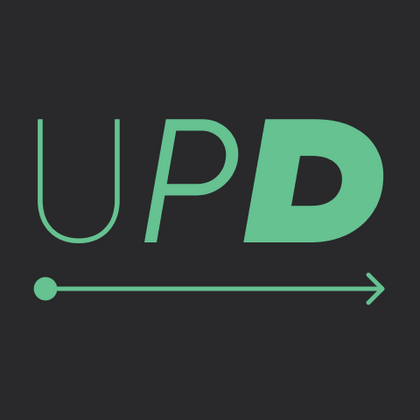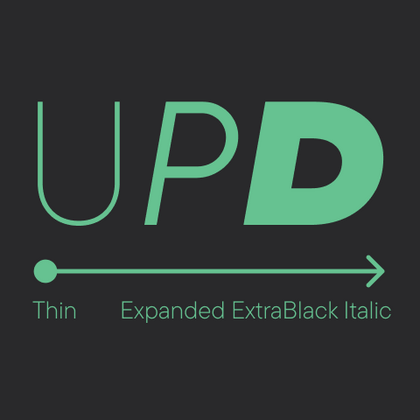
Обновленные шрифты
Коллекция шрифтов TypeType постоянно развивается — мы регулярно улучшаем существующие гарнитуры и расширяем их функциональность. Благодаря этому дизайнеры получают актуальные инструменты с поддержкой современных стандартов типографики.
Среди новинок вы найдете обновленные шрифты с расширенной языковой поддержкой, включая редкие символы и диакритические знаки для разных языков. Каждая такая гарнитура проходит тщательное тестирование, чтобы гарантировать безупречное качество отображения во всех проектах.
TT Norms® Pro — TT Нормс Про
«TT Norms» является зарегистрированным товарным знаком. «Pro» произносится как «про», и является разговорным сокращением слова «профессиональный».
TT Commons™ Pro — TT Коммонс Про
«TT Commons» является зарегистрированным товарным знаком. «Pro» произносится как «про», и является разговорным сокращением слова «профессиональный».
TT Hoves Pro — ТТ Ховс Про
Произносится «ТТ Ховс Про». «Hoves» — производное слово от horizontal (с английского «горизонтальный») и vertical (с английского «вертикальный»). «Pro» произносится как «про», и является разговорным сокращением слова «профессиональный». Буквы «TT» являются аббревиатурой названия компании.
TT Norms® Pro Serif — TT Нормс Про Сериф
«TT Norms» является зарегистрированным товарным знаком. «Pro» произносится как «про», и является разговорным сокращением слова профессиональный. «Serif» произносится как «сериф», в переводе с английского «антиква».
TT Nooks Serif — ТТ Нукс Сериф
Произносится «ТТ Нукс Сериф». «Nooks» — производное слово от nook, в переводе с английского «закоулок». «Serif» произносится как «сериф», в переводе с английского «антиква». Буквы «TT» являются аббревиатурой названия компании.
TT Nooks Serif — акцидентная новостильная антиква с лёгким налётом эгоцентричности. У неё острый и твёрдый, при этом элегантный и статный характер.
TT Chocolates — ТТ Чоколитс
Произносится «ТТ Чоколитс». «Chocolates» — производное слово от chocolate, в переводе с английского «шоколад». Буквы «TT» являются аббревиатурой названия компании.
TT Chocolates — изящный гуманистический гротеск сo сбалансированными пропорциями, близкими к классическим. Шрифт с приятным дружелюбным характером, который интуитивно воспринимается как что-то знакомое.
TT Nooks Script — ТТ Нукс Скрипт
Произносится «ТТ Нукс Скрипт». «Nooks» — производное слово от nook, в переводе с английского «закоулок». «Script» произносится как «скрипт», в переводе с английского «курсив». Буквы «TT» являются аббревиатурой названия компании.
TT Nooks Script — шрифт с уникальным рисунком, который не имеет прямых аналогов.
TT Supermolot Neue — ТТ Супермолот Нью
Произносится «ТТ Супермолот Нью». «Supermolot» — производное слово от super (с английского «супер») и molot (транслитерация слова «молот»). «Neue» — в переводе c немецкого «новый». Буквы «TT» являются аббревиатурой названия компании.
TT Supermolot Neue — технологичный модульный гротеск с футуристическим настроением и мощным функционалом. Яркость его характера сочетается с универсальностью применения.
TT Rationalist — ТТ Рационалист
Произносится «ТТ Рационалист». «Rationalist» — в переводе с английского «рационалист». Буквы «TT» являются аббревиатурой названия компании.
TT Rationalist — функциональный и оригинальный брусковый шрифт с актуальным рисунком. Он универсален и подходит как для заголовков, так и для массивов текста.
TT Commons™ Classic — TT Коммонс Классик
«TT Commons» является зарегистрированным товарным знаком. «Classic» произносится как «классик», в переводе с английского «классический».
TT Commons™ Classic — универсальный геометрический гротеск для широкого круга задач.
TT Runs — ТТ Ранс
Произносится «ТТ Ранс». «Runs» — производное слово от run, в переводе с английского «бег». Буквы «TT» являются аббревиатурой названия компании
TT Runs — это выразительный шрифт, который идеально впишется в проекты со спортивной тематикой. При этом гарнитура отлично подойдет и для других современных проектов: после обновления сфера ее применения значительно расширилась.
TT Ramillas — ТТ Рамильяс
Произносится «ТТ Рамильяс». «Ramillas» — производное слово от испанского «ramilla», что переводится как «стебель» . Это название отражает визуальные особенности шрифта: тонкие, изящные, расширяющиеся к концам засечки, напоминающие веточки . Буквы «TT» являются аббревиатурой названия компании.
TT Ramillas — стильная и современная антиква. Включает уникальные декоративные начертания и буквицы с цветочным орнаментом.